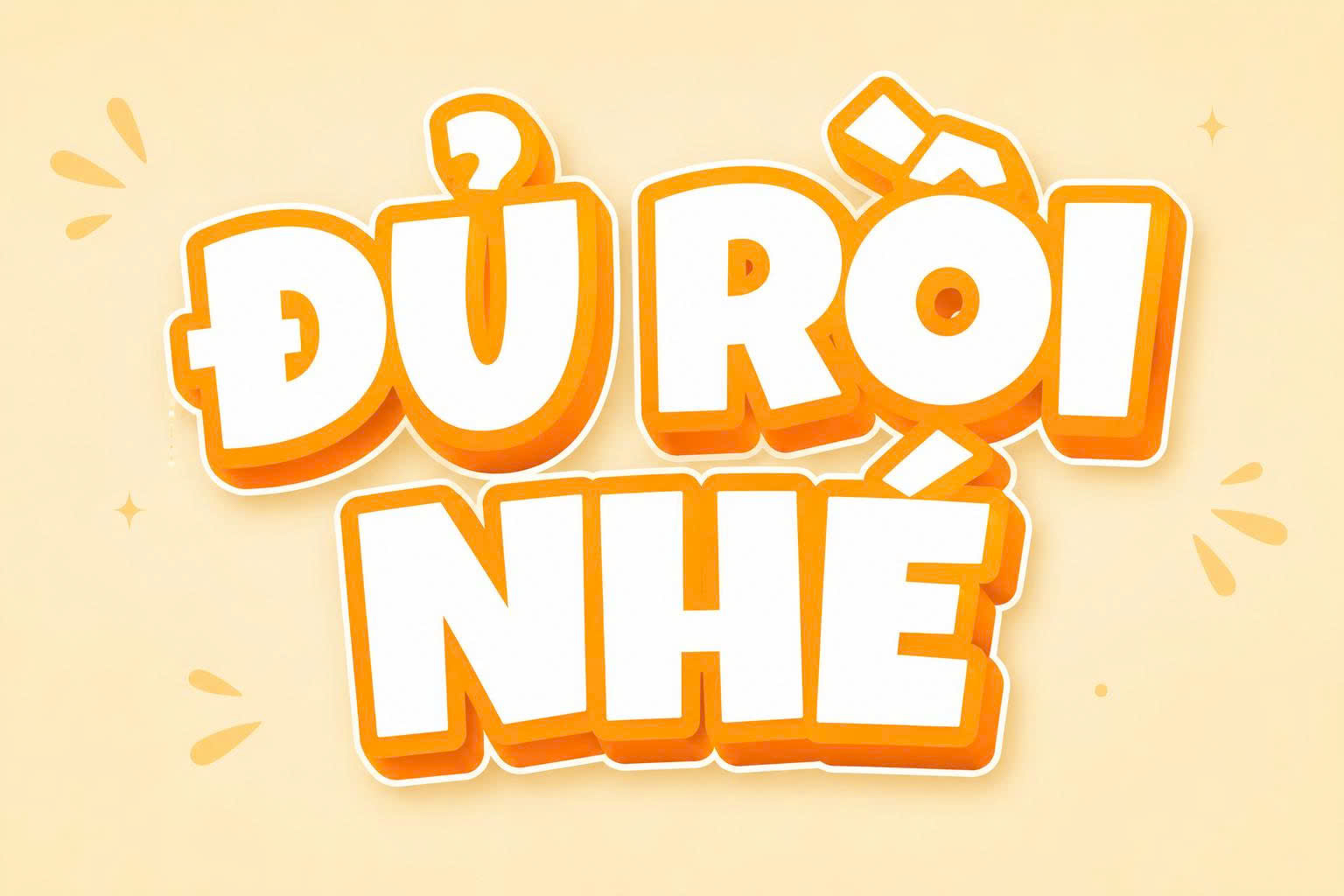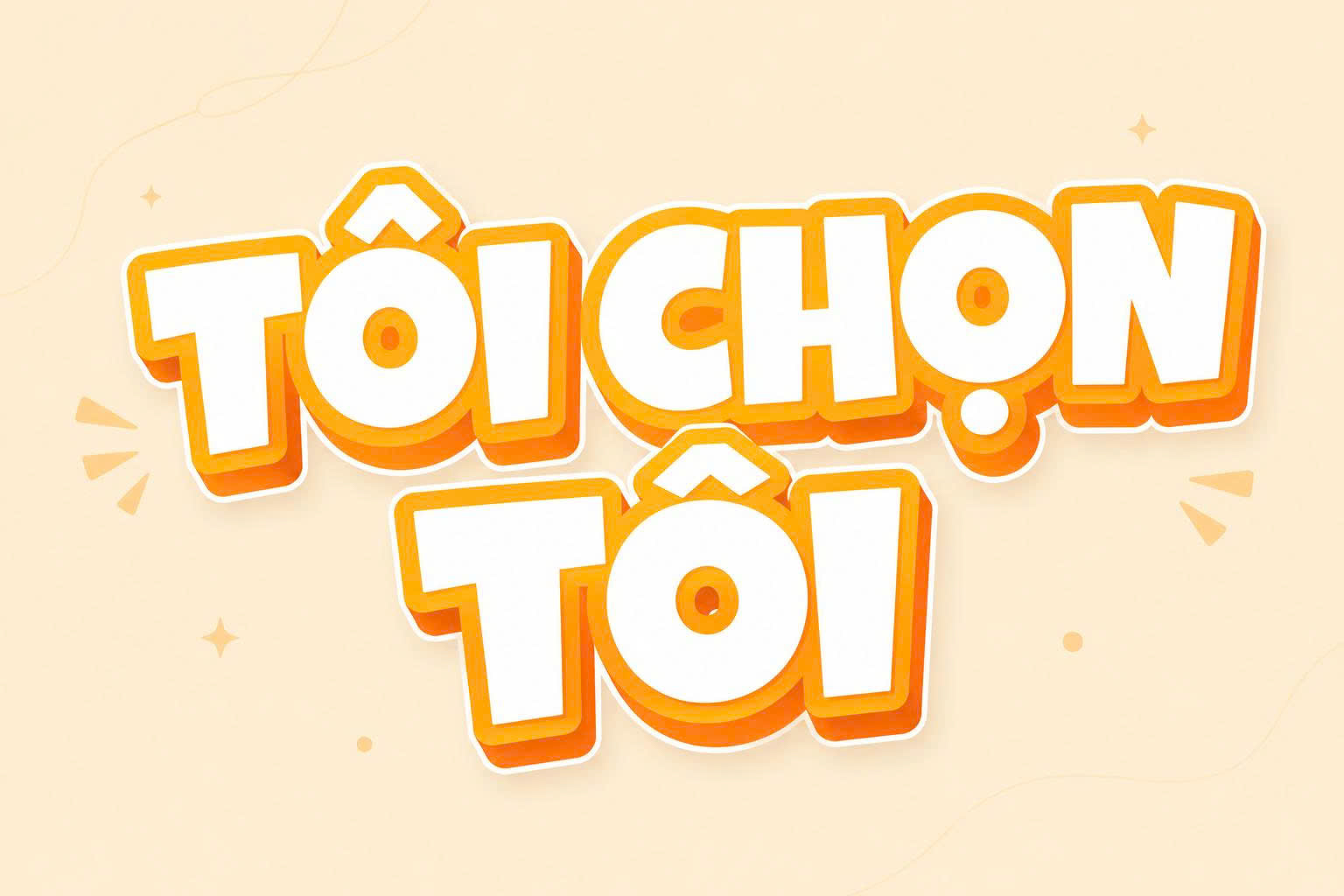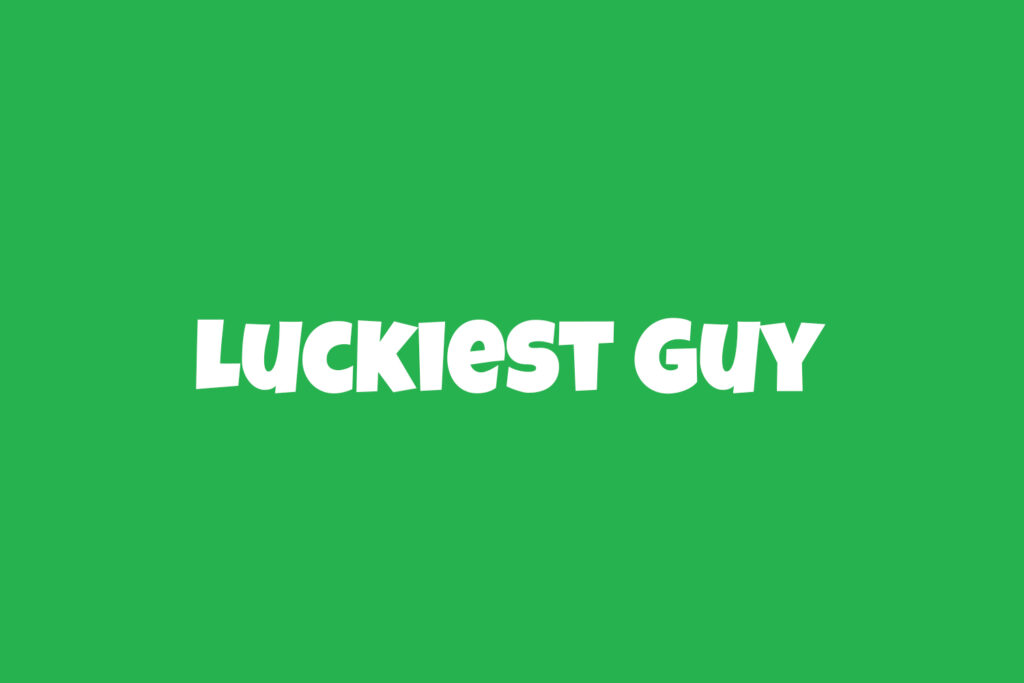
Luckiest Guy font Việt hóa là bộ phông chữ thuộc dòng Heavy Retro Display do Brian J. Bonislawsky sáng tạo, lấy cảm hứng từ nghệ thuật vẽ chữ thủ công trên các tấm áp phích điện ảnh và biển quảng cáo thương mại nước Mỹ thập niên 1950. Với các khối chữ dày dặn, đường chân đế nhún nhảy tự do và tinh thần lạc quan, phông chữ này là chất liệu trực quan tuyệt vời để các kiến trúc sư, nhà thiết kế mang lại sự phấn khởi cho các bản vẽ phối cảnh quán ăn nhanh container, công viên giải trí ngoài trời hay biển hiệu homestay thanh xuân.
Khối hình đầm chắc và nhịp điệu Hollywood thập niên 1950 của Luckiest Guy font Việt hóa
Điểm cuốn hút của Luckiest Guy font Việt hóa nằm ở sự kết hợp giữa trọng lượng nét chữ đậm đặc và nhịp điệu chữ cái không thẳng hàng một cách có chủ đích, mô phỏng sinh động sự ngẫu hứng của các nghệ sĩ vẽ bảng hiệu xưa. Cấu trúc ký tự sở hữu các góc vát mềm mại, loại bỏ cảm giác khô khan của các khối hình học công nghiệp để mang lại vẻ ngoài thân thiện, tràn đầy năng lượng và dễ mến.
Sự ổn định về mặt thị giác của dòng font này tạo nên khả năng chiếm lĩnh không gian hiển thị từ cự ly rất xa. Khi xuất hiện trên các bề mặt vật liệu kiến trúc hiện đại như vách tôn sóng container sơn màu đỏ tươi, tấm alu vàng chanh hay mặt biển hiệu đèn neon uốn viền trong các căn nhà lắp ghép thế hệ mới, Luckiest Guy tạo nên điểm nhấn kiến trúc giàu sức hút.
| Phân loại phong cách | Retro Display / Comic Heavy / 1950s Hollywood |
| Mục đích phù hợp | Biển tên quán ăn nhanh, poster lễ hội, logo ki-ốt |
Tư vấn từ chuyên viên: Luckiest Guy sở hữu nét chữ dày và độ phủ bề mặt rất lớn. Để bản thiết kế đạt hiệu quả thẩm mỹ tốt, bạn nên sử dụng phông chữ này cho các tiêu đề chính, tên thương hiệu hoặc khẩu hiệu ngắn.
Nhờ vẻ ngoài vui nhộn và tính gợi hình mạnh mẽ, bộ phông chữ này mang lại giá trị thực tế lớn trong khâu tạo điểm nhấn cho các công trình hiện đại:
- Biển hiệu mặt tiền cho Quán Ăn Nhanh và Tiệm Nước Container: Những khối chữ đầm chắc của Luckiest Guy rất ăn ý khi gia công chữ nổi bằng mica màu sắc gắn đèn LED hắt chân trên nền tôn sóng, mang lại diện mạo rực rỡ và thu hút khách hàng ghé thăm thưởng thức đồ ăn.
- Hệ thống biển chỉ dẫn Khu cắm trại Dã ngoại và Công viên giải trí: Phông chữ này khi in trên các bảng alu phản quang hoặc sơn trực tiếp lên vách gỗ sẽ giúp không gian toát lên chất phiêu lưu vui nhộn, tạo nhiều góc chụp ảnh kỷ niệm bắt mắt.
- Trang trí không gian sinh hoạt chung Homestay giới trẻ: Bạn có thể dùng phông chữ này để làm tranh cổ động, khẩu hiệu truyền cảm hứng tại phòng khách căn nhà lắp ghép, khơi gợi tinh thần lạc quan và tạo bầu không khí ấm cúng cho các bạn trẻ.
03 Lưu ý bố cục Luckiest Guy regular font Việt hóa luôn bắt mắt và cân đối
Để khai thác hiệu quả vẻ đẹp của dòng font retro hoạt hình này mà không gây cảm giác rối mắt cho bản vẽ, người thiết kế nên lưu tâm một số kinh nghiệm sau:
- Bố trí khoảng thở rộng rãi: Do cấu trúc chữ có độ nở ngang lớn và các nét dày, bạn nên chừa khoảng trống thoáng đãng xung quanh tiêu đề để các con chữ có không gian bộc lộ năng lượng vui tươi, tránh chèn ép bởi các chi tiết đồ họa phụ trợ.
- Hạn chế dùng cho đoạn văn bản dài: Luckiest Guy regular font Việt hóa chỉ tối ưu cho các cụm từ ngắn từ 1 đến 4 từ. Việc lạm dụng cho các đoạn văn bản giải thích chi tiết sẽ làm giảm đáng kể khả năng đọc hiểu của người xem.
- Kết hợp cùng gam màu Pop Art nổi bật: Phông chữ phát huy hiệu quả thị giác cao khi phối cùng các tông màu tương phản mạnh như vàng nghệ – đỏ cờ, xanh dương – cam cà rốt hoặc trắng tuyền trên nền xám than chì mờ.